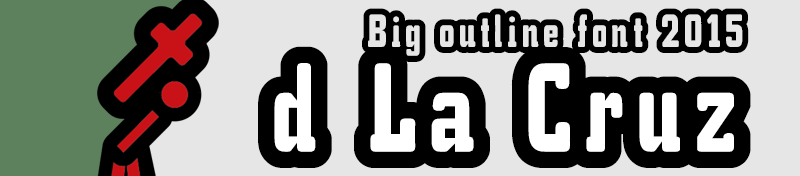
Font name: | d La Cruz |
Tipografía condensada semi-serif con una grueso borde. =========== Condensed semi-serif typeface with big outline. =========== • Sólo para uso personal. • Licencia comercial disponible en mi web • Only for personal use. • Commercial license for sale on my website d La Cruz, big outline font >>: https://defharo.com/fonts/d-la-cruz-font/ |